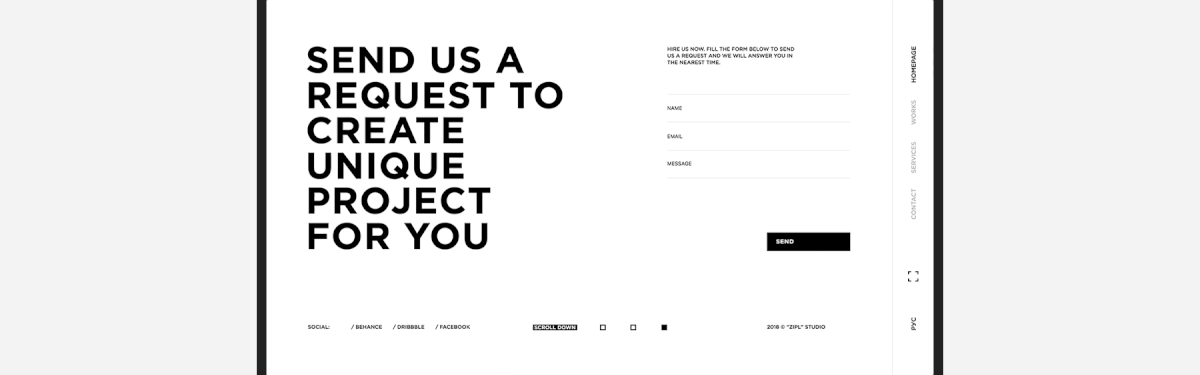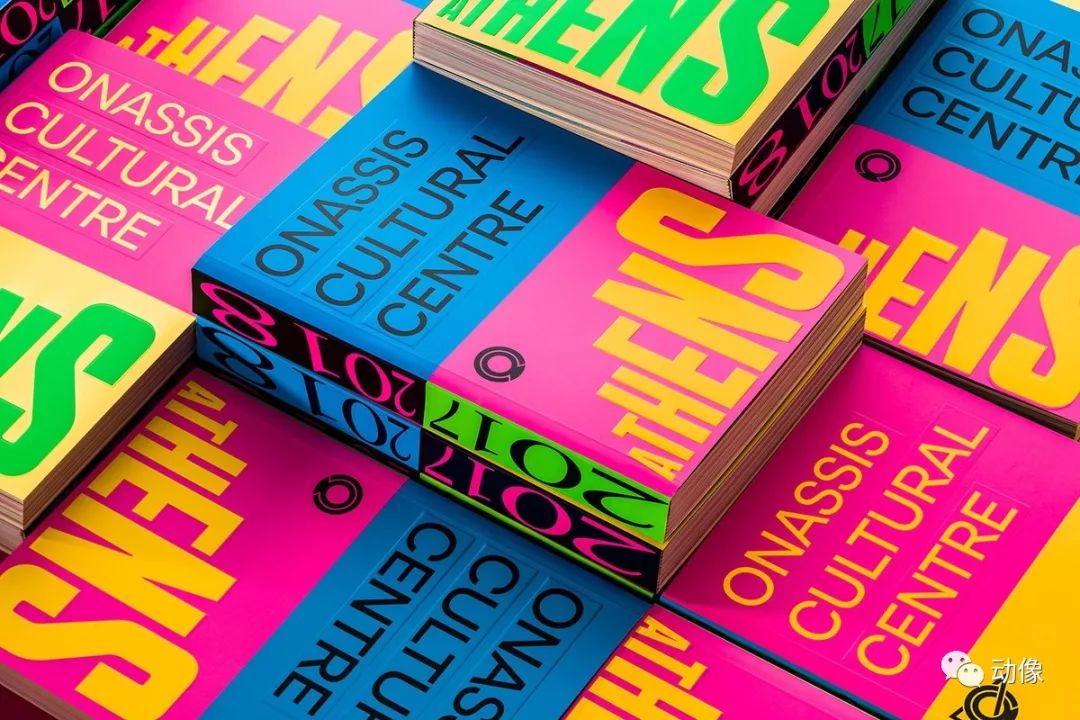
2019设计趋势,从颜色、排版,到图案、动效,无不细化深入
不过柚子还是未卜先知,提前整理了一些大神们总结的2019设计趋势,从颜色、排版,到图案、动效,无不细化深入。
1、夸张用色
2019将继续鲜明的色彩这一趋势,并且更夸张。潘通色卡趋势显示,2019 年,如果想让你的工作脱颖而出,请大胆用过饱和色。
2、非对称性
你可以在排版、几何形状或 3D 渲染,创建一个不对称的视觉效果,记住用户首先会看到较大的元素。
3、结合人物
将各种各样的创意与人物结合在一起,可以带来独特的角度,最后达到惊人的效果。
4、继续渐变
渐变风在2019 依然流行,Apple 和 Instagram 也在他们的品牌中使用了渐变,绝配啊有木有。
5、轴侧设计
过去几年,我们已经看到轴侧设计趋势,2019 年随着插图占领所有设计领域,轴测图依然是趋势。
6、 移动端优先
移动端网站是现在的首选,谷歌是第一个实现的公司。优先为移动端用户设计网站,然后再考虑桌面端版本。
7、少即是多
负空间在所有设计领域都适用,之前在极简设计学不会?这里有25种方法,一键打包给你也提过,高级感就是要极简。
8、插画设计
根据最新数据,插画设计比任何形式的摄影效果好7倍,且呈继续增长的趋势,一个好的插画师,可以给品牌带来活力。
9、 直观的图标
建立视觉层级,将用户的注意力转向你希望的地方。例如看到动态线性图标,人们会自然联想到服务。
10、动效爆发
动效迎来巨大发展,你可以在网站、广告或 App 中,轻易找到它们的身影。一个按钮转换,一个悬停效果,都发挥了巨大的作用。
11、将字体替代成图片
文字逐渐成为公众关注的焦点,许多品牌,已将文字替代成了图片,更显精致。
12、 3D设计
在过去的一年里,3D 设计取得了巨大发展。无论什么产品使用 3D 动效,都会增加表现力,有很高的转化率。
13、大胆排版
在每年的预测中,大胆排版都成了一种趋势。使用极简主义大字,是个不错的选择,否则看起来会很挤,且没有吸引力。
14、 独特字体
很多大品牌都有自己的字体,代表了自己的性格独一无二。
15、颜色通道
今年我们就看见了这一趋势,但在 2019 年仍然是新鲜的概念,使用颜色通道可以创建显著的视觉效果。
16、动态Logo
所有的设计领域都离不开“动”,在logo中也不例外,因为太吸引人了。
17、非传统的包装设计
用非传统材质包装,是设计领域的重要方向。使用可降解、可食用的材料,是创新品牌的理念。
18、大字为王
大字体设计是 2019 年必然趋势,一个大胆的封面,一个大词就够了。比如大小字母的组合,就是一个漂亮的设计。